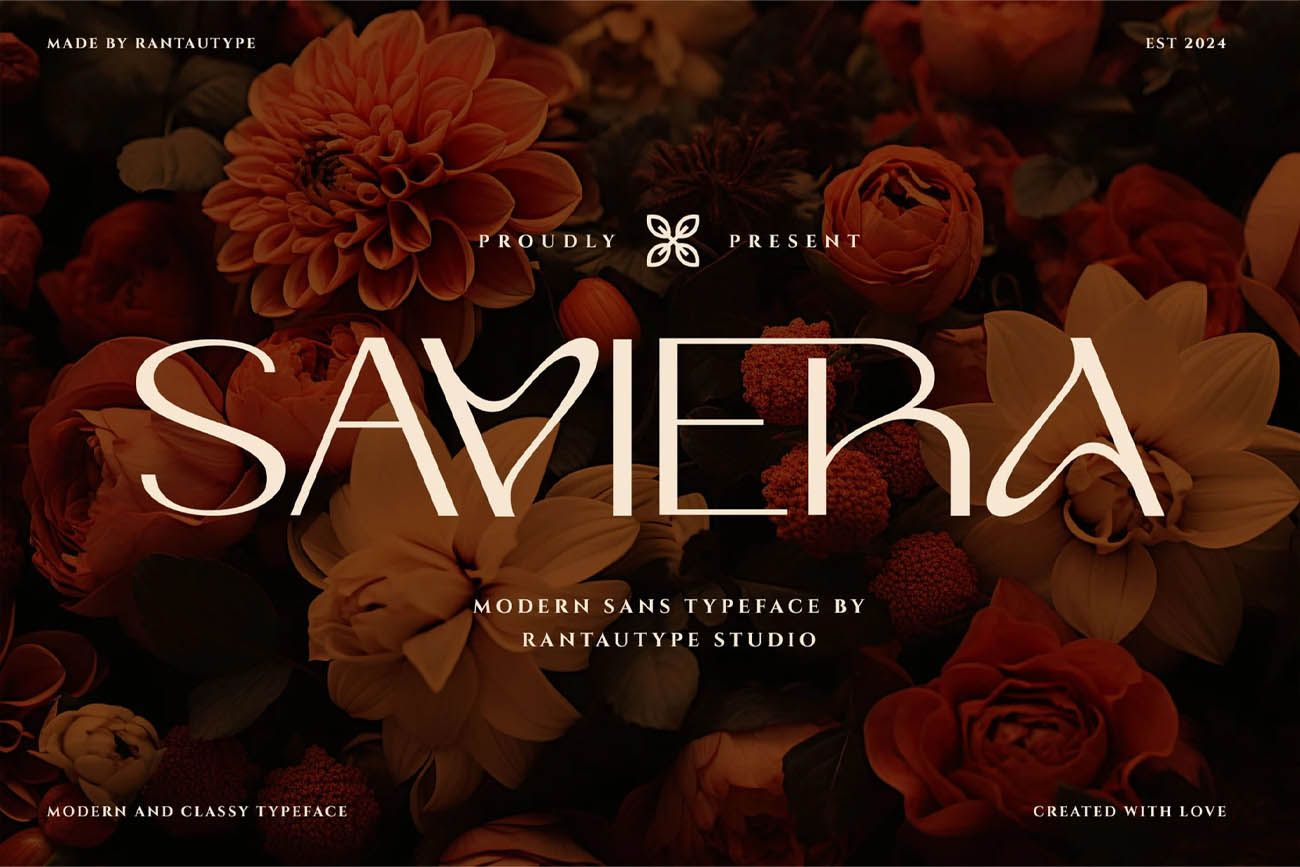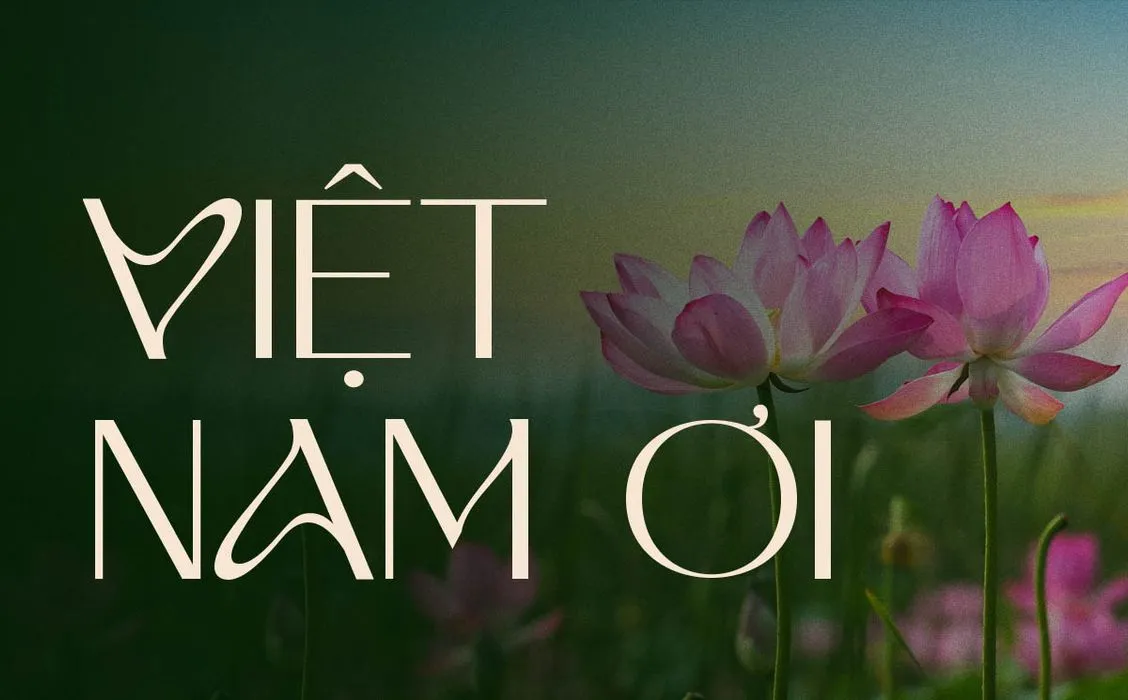
Bản TH Saviera Regular Việt hóa được thực hiện bởi Phạm Sơn – Admin của S99.vn và Fontdep.vn, hỗ trợ đầy đủ tiếng Việt với dấu thanh chuẩn xác, không lỗi ký tự. Điều này giúp bạn dễ dàng ứng dụng font trong thiết kế mà vẫn giữ nguyên tinh thần và vẻ đẹp của bản gốc.
Kiểu dáng hiện đại: Các ký tự không chân được thiết kế tối giản nhưng có điểm nhấn ở các nét cong, đường cắt chéo và khoảng hở tinh tế.
Đường nét thanh mảnh: Mỗi ký tự mang cảm giác nhẹ nhàng, thanh lịch, phù hợp với các thiết kế cao cấp.
Tính ứng dụng cao: Dùng tốt cho logo thương hiệu, tiêu đề tạp chí, thiệp mời cưới, bao bì mỹ phẩm, lookbook hoặc các ấn phẩm thời trang.
Việt hóa trọn bộ: Hỗ trợ đầy đủ chữ cái, số, dấu câu và ký tự đặc biệt, đảm bảo trải nghiệm thiết kế liền mạch.
Saviera Regular đặc biệt phù hợp khi bạn muốn tạo ấn tượng tinh tế và chuyên nghiệp. Font có thể kết hợp cùng tone màu tối giản hoặc sang trọng để tạo nên các sản phẩm thiết kế nổi bật, dễ ghi dấu trong tâm trí người xem.